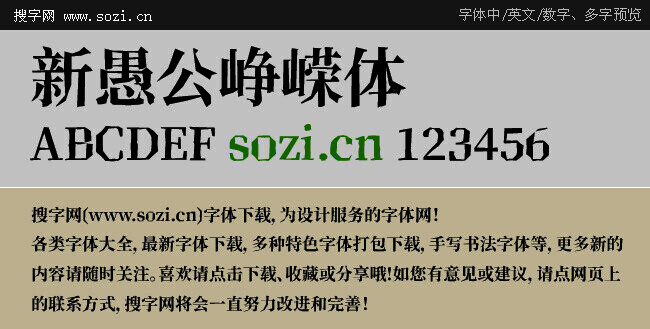
新愚公崢嶸體
搜字網(wǎng)給大家提供一款新愚公崢嶸體中文字體下載,新愚公崢嶸體是新愚公在業(yè)余時間對思源宋體進行改造的一款字體。這款字體加入了隨機的扭曲效果,讓字體看去上有一種歪歪扭扭的視覺效果,給人一種做舊復古的感覺,別有一番風味。字體適合兒童廣告設(shè)計、卡通海報設(shè)計、包裝設(shè)計等應用。